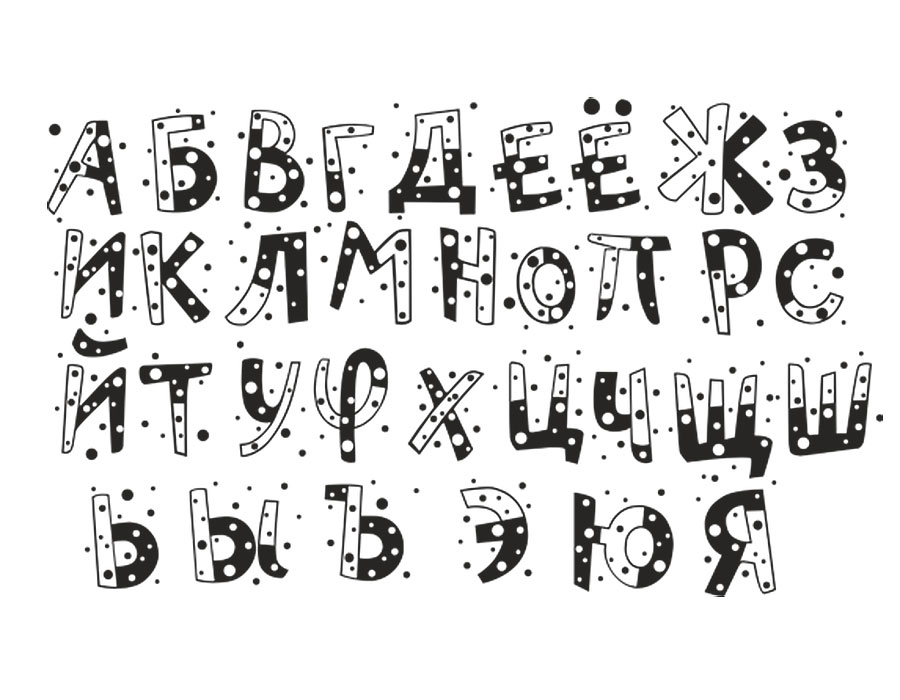
Шрифт — графический рисунок начертаний букв и знаков, составляющих единую стилистическую и композиционную систему, набор символов определенного размера и рисунка. В узком типографском смысле шрифтом называется комплект типографских литер, предназначенных для набора текста. Группа шрифтов разных видов и кеглей, имеющих одинаковое начертание, единый стиль и оформление, называется гарнитурой.
Красивые бесплатные русские детские шрифты.
Шрифты для комиксов и мультяшные шрифты Детские стили кириллицаХочу представить вашему вниманию небольшую подборку, в которую вошли , а так же мультяшные шрифты
1. Один из , которые используют в комиксах. В нем только прописные буквы, легкие небрежность, и наклон, и разная толщина линий. В общем в баллонах чьих-то комиксов вы его наверняка встречали, попробуйте вставить в свои.
2. Если переводить название этого шрифта, получится что-то типа “куриная задница”. Я не знаю почему так. Мне этот шрифт приглянулся необычной формой и . Думаю вполне уместен в каких-то мультипликационных заголовках и всяком таком. Имеет как прописные, так и строчные символы.
3. Брутально угловатый, резкий, жирный шрифт. Тоже видал где-то в комиксах. Смотрится четко и гармонично особенно в окружении экшена. Традиционно для комиксовских шрифтов отсутствуют строчные символы.
4. Этот мне напоминает шрифт из старых мультиков, типа “Ну, погоди!”. Ну там когда авторов перечисляют в титрах. Похож очень по-моему. В общем для стенгазет, новых годов и прочих подобных детских тем. Подойдет идеально.
5. Еще один типичный шрифт из комиксов. Во всевозможных человеках пауках, росомахах, марвелах и прочих супергероях вы его обязательно встретите. Строчных традиционно нет.
6. Сказочно – эксцентричный, так бы я его назвал. Очень понравился этот шрифт. Асимметрия его не мешает чтению, но втыкает большую изюмину в его мякоть. Прекрасно подойдет для оформления каких-нибудь волшебных сказок или заклинаний. Ну или еще для чего-то.
7. Утонченный, резковатый, слегка разнузданный. Не знаю где я его видел, то ли в комиксах, то ли в мультиках?
8. Каменно – треснутый шрифт. Подойдет, естественно, для легенд о . Ну или для заголовков о чем-нибудь каменно-толстом например. Присутствует в 2-х вариантах – залитый и контурный с тенью.